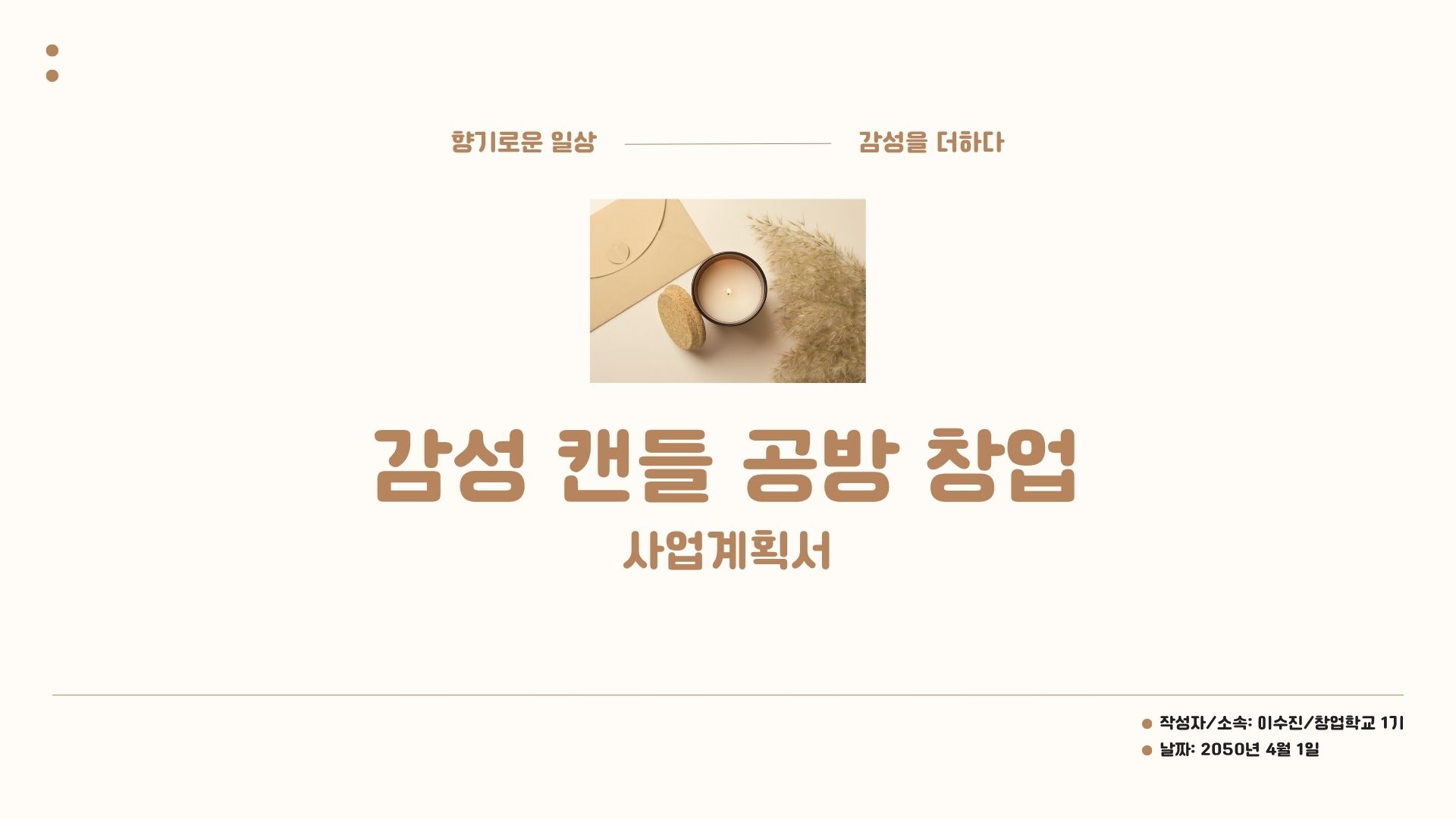
카페24 써라운드 — Cafe24에서 배포하는 무료 폰트입니다. 글자의 모서리와 획 끝을 모두 둥글게 굴려, 뉴트로 굴림의 인상을 내는 디스플레이 서체
카페24가 2020년 7월에 공개한 서체로, 나온 배경이 뚜렷합니다. 이커머스 플랫폼인 카페24가 소상공인의 콘텐츠 제작을 돕겠다는 취지로 만든 글꼴이고, 공개 당시 카페24의 무료 서체는 이걸로 열아홉 종이 됐습니다. 카페24가 운영하는 이미지 편집 서비스 에디봇에 기본 글꼴로 들어가 있기도 합니다.
이름대로 글자의 모서리와 획 끝을 모두 둥글게 굴린 것이 특징입니다. 굵은 획에 둥근 마감이 붙어 부드러우면서도 존재감이 큽니다. 파일에서 재어 보면 받침 유무에 관계없이 높이가 일정한 네모틀이고 낱자는 정사각형에 가까우며, 가로세로 획 굵기가 고른 민부리입니다. 현대 한글 11,172자를 모두 담았습니다.
굵기는 굵은 써라운드와 가는 써라운드 에어 두 갈래로 나옵니다. 상품 상세페이지나 이벤트 배너의 제목처럼 짧고 굵게 읽혀야 하는 자리를 겨냥한 서체라 그 목적에는 잘 맞고, 획이 굵고 둥근 만큼 긴 본문에 깔면 답답해집니다. BI와 CI 제작까지 허용되는 넓은 라이선스도 장점입니다.